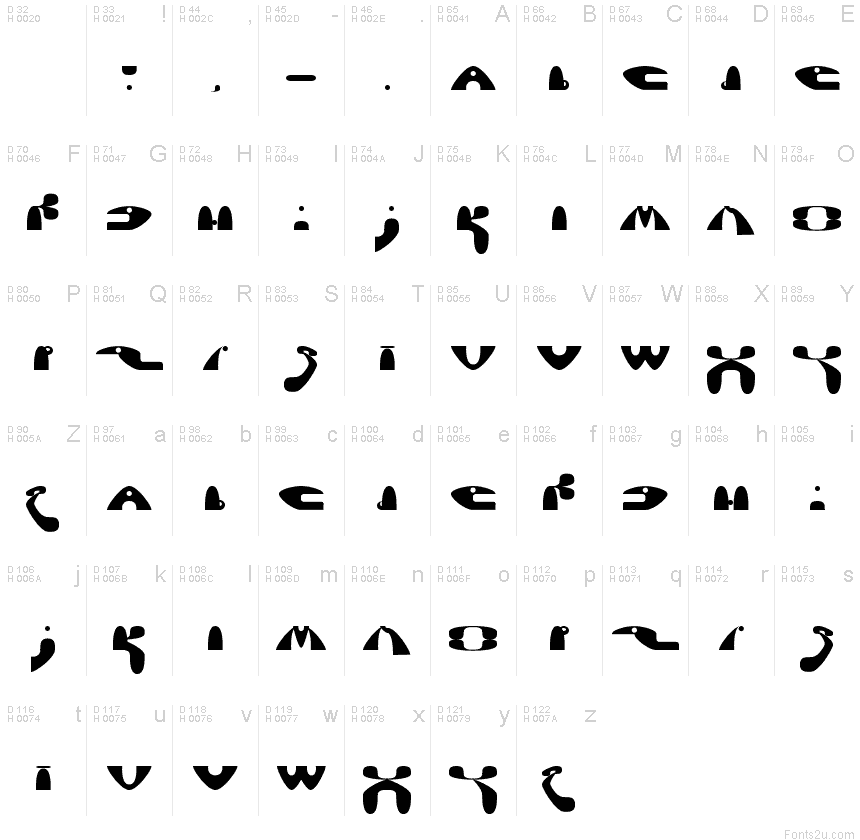
Saz, dílo Jasona Skooga, je bezplatný psychedelický font typu display s hutnou siluetou připomínající plakáty minulé éry. Písmena sází na velké černé křivky, houbovité vršky a kapkovité koncovky, zatímco špičatý oblouk a kruhový výřez v „A“ dodávají abecedě lehce surrealistický rytmus evokující lávovou lampu.
Tento bezplatný font se skvěle hodí na retro hudební letáky, klubové plakáty, obaly desek, festivalový branding a titulky, kde k navození atmosféry stačí jen pár znaků. Nejlépe funguje v krátkých nadpisech, logách a monogramech, protože ty nadýchané křivky a zvláštní drobné detaily udělají spoustu parády i bez dlouhého textu.